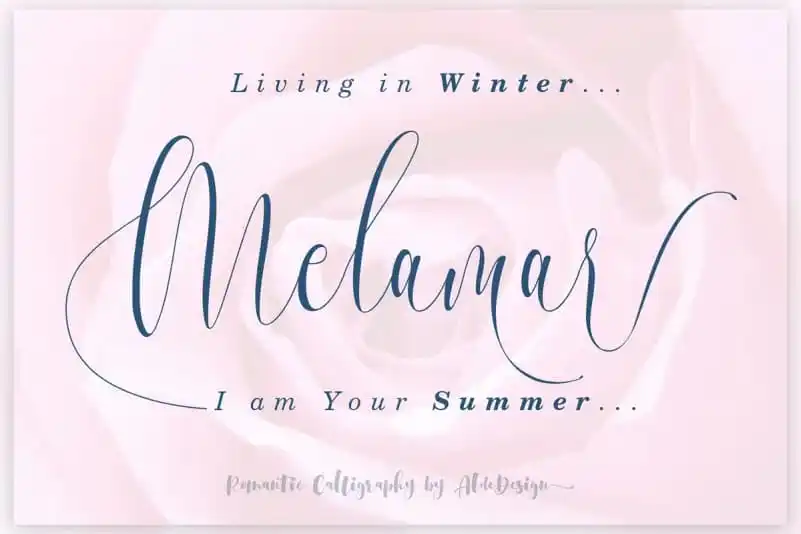
Melamar Calligraphy Font – Fonte Grátis
Melamar Calligraphy Font
A “Melamar Calligraphy Font” é uma elegante tipografia de calligrafia lançada pela aldedesign, conhecida por sua delicadeza e sofisticação. Este tipo de fonte é perfeita para aqueles que buscam adicionar um toque romântico moderno aos seus projetos, seja para assinaturas, selos, logotipos, embalagens ou até mesmo para cartazes e identidade visual. Seu design arredondado e único oferece uma opção versátil para diversos usos, incluindo o cabeçalho de página, convites, selos de casamento, estampas em têxteis e até mesmo como logotipos para camisas personalizadas. Ideal tanto para designers quanto para quem busca um toque diferente nas suas criações gráficas.